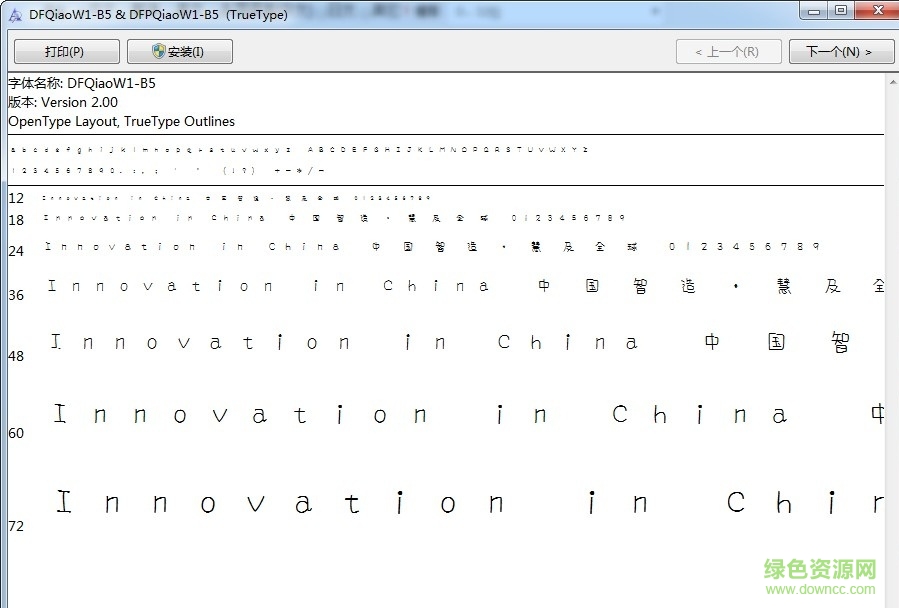
華康巧風(fēng)體簡(jiǎn)體
華康巧風(fēng)體字體是一款趣味性較足的字體哦,這款字體看起來非常輕巧,并且字形也很清新,有需要的就來綠色資源網(wǎng)下載吧!
華康巧風(fēng)字體介紹
華康巧風(fēng)體,這字體是一款美術(shù)風(fēng)格的繁體字庫(kù),摘自華康最新出品的《華康手書風(fēng)II-字得其樂》,字庫(kù)為大五碼(BIG5),臺(tái)港澳地區(qū)的繁體系統(tǒng)中使用,所以如果在簡(jiǎn)體中文系統(tǒng)中使用時(shí),必須直接輸入繁體字,才能正常顯示所有的文字,并且在字體選擇欄中顯示的字體名稱不是中文,顯示名稱為:DFQiaoW1-B5或DFPQiaoW1-B5。